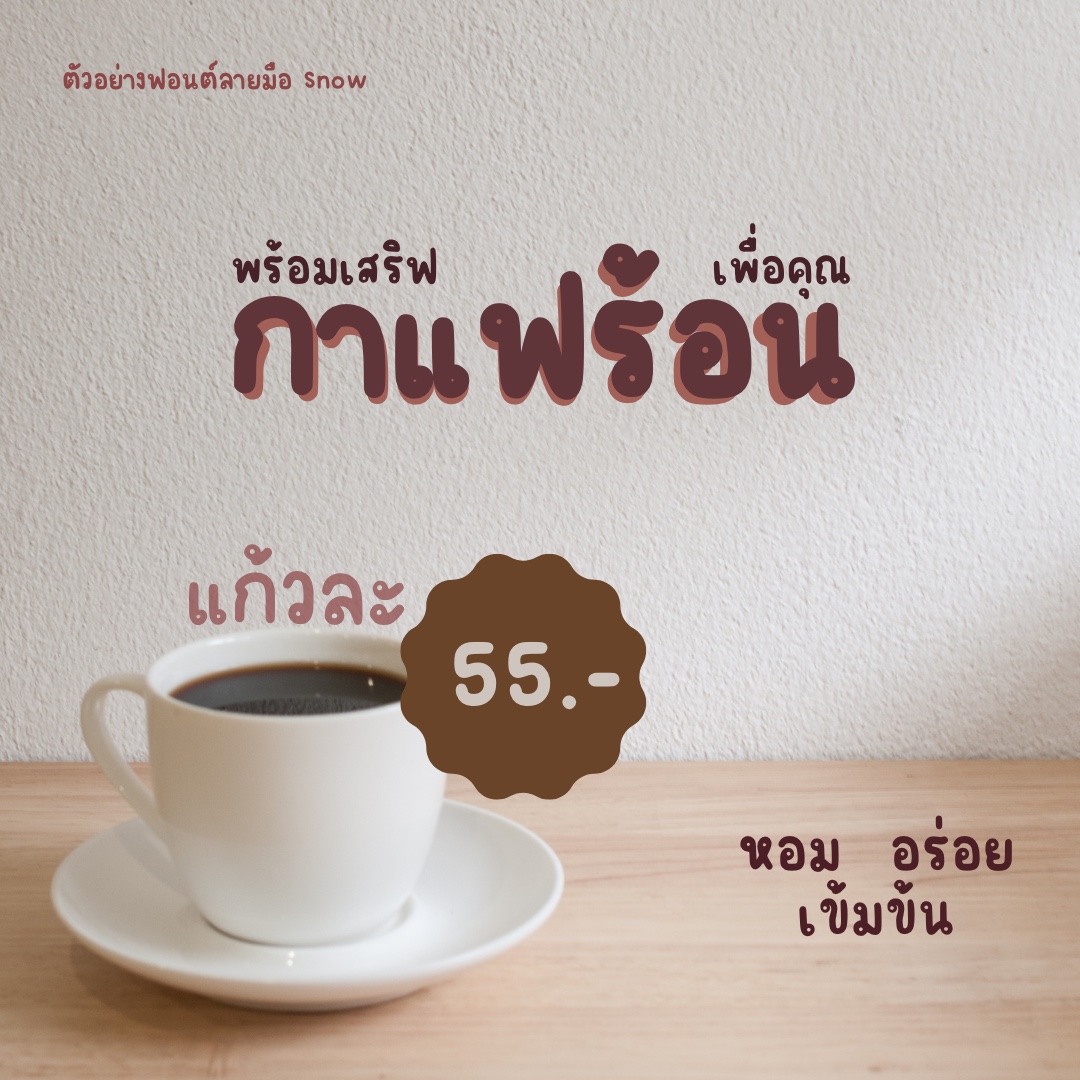
Snow
แจกฟรี!!!! ฟอนต์ลายมือ Snow
Snow เป็นฟอนต์ลายมือเรียบ ๆ น่ารัก ๆ น่ามองใช้ได้เรื่อย ๆ ไม่น่าเบื่อ แม้จะเป็นฟอนต์เรียบ ๆ แต่ยังมีความสดใสซุกซนเป็นตัวหนังสือที่มีความยืดหยุ่น สร้างสรรค์แบบไม่สิ้นสุด